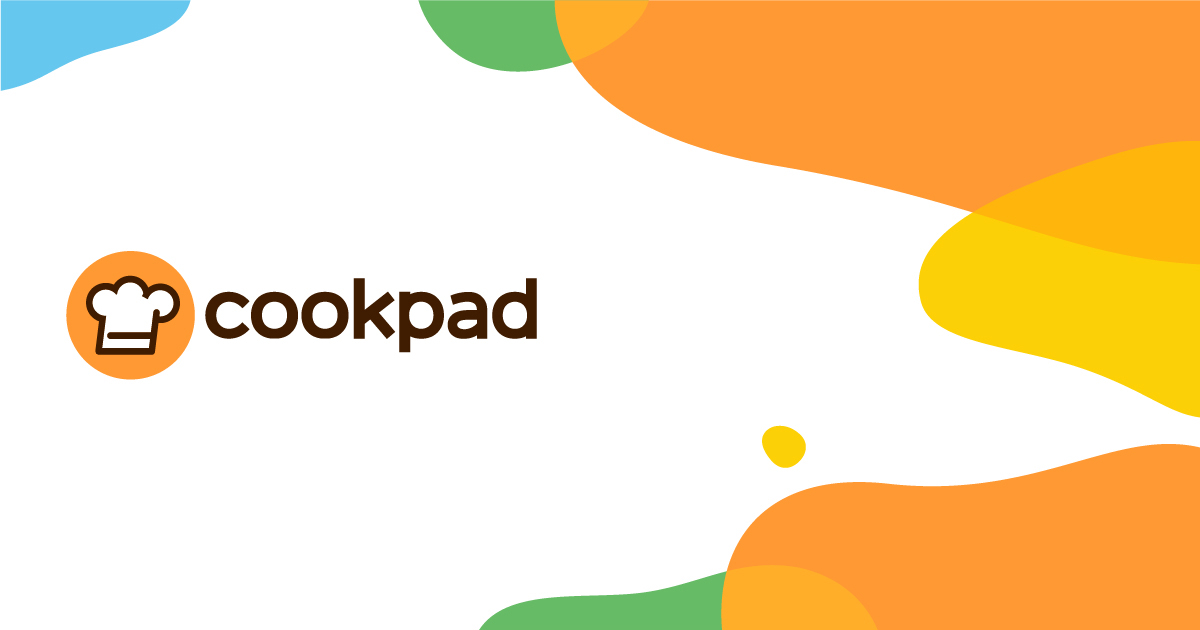
クックパッドがコーポレートブランドデザイン「Organic」を策定し、オリジナルフォント「Cookpad Sans」を作成
クックパッドは、ミッションである「毎日の料理を楽しみにする」をより視覚的、感覚的に伝えることを目的に、コーポレートブランドデザイン「Organic」の策定および、オリジナルコーポレートフォント「Cookpad Sans」の作成を行ったことを2022年7月21日に発表した。
新たなコーポレートブランドデザインは、柔らかで、温かみのある様々な形状/有機的(Organic)な色面の構成により、多様性を受け入れるクックパッドのプラットフォームの中で、つくり手が楽しんでいる躍動感を表現されている。
「Cookpad Sans」の作成はフォントワークスが協力しており、コーポレートブランディングをデザインの力で牽引し、ミッションである「毎日の料理を楽しみにする」をより多くの人に伝えていく。
あわせてOrganicを適用した新しいコーポレートサイトもリリースした。
コーポレートブランドデザイン策定の背景
クックパッドでは「毎日の料理を楽しみにする」をミッションとし、世界74カ国、32言語で提供している料理レシピ投稿・検索サービス「クックパッド」をはじめとした、料理にまつわる課題を解決する事業を展開している。その中で、今まで以上に迅速にミッション実現に近づくためには、その背景にある当社の思いや、さまざまなつくり手が楽しんでいる姿を、より多くの人に伝え、共感していただく必要があると考え、「多様なつくり手を受け入れ、つながることで生まれる『料理の楽しさ』を感じさせるデザイン」をコンセプトに、新たなコーポレートブランドデザイン「Organic」の策定および、オリジナルコーポレートフォント「Cookpad Sans」を作成した。
あわせてOrganicを適用した、新しいコーポレートサイトを公開している。
コーポレートブランドデザイン「Organic」
柔らかで、温かみのある様々な形状/色による有機的(Organic)な色面の構成による、クックパッドのコーポレートブランドデザインを策定した。多様性を受け入れるクックパッドのプラットフォームの中で、つくり手が楽しんでいる躍動感を表現している。
オリジナルコーポレートフォント「Cookpad Sans」
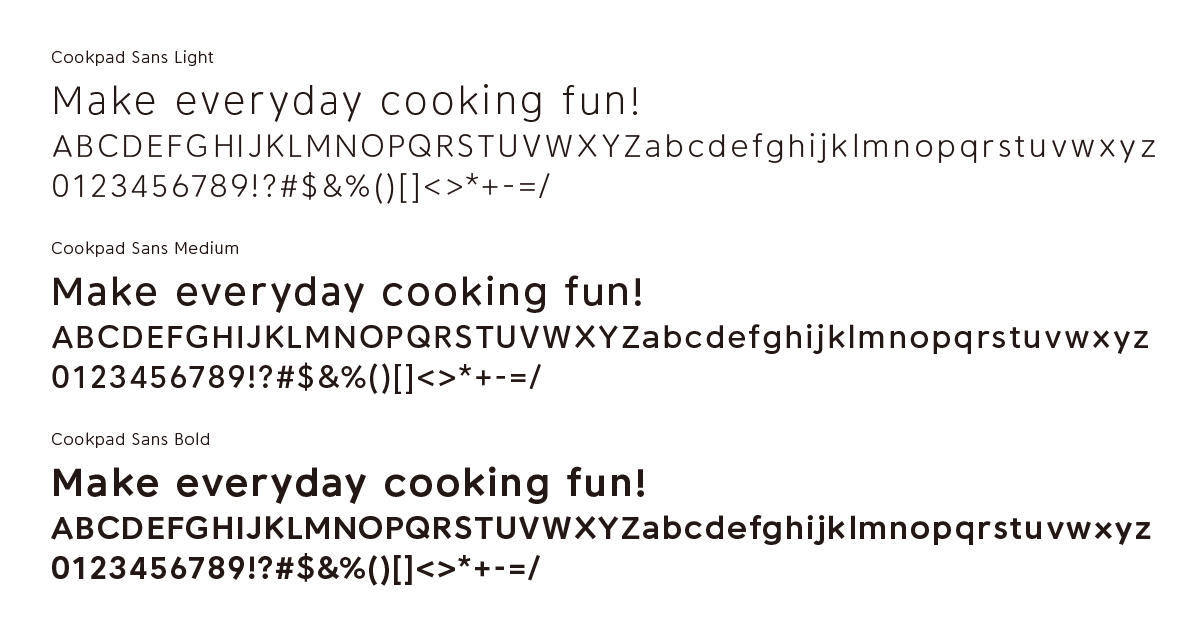
クックパッドのロゴタイプフェイスを起点とした欧文フォントを、フォントワークスに協力により、作成した。
新しいコーポレートサイト
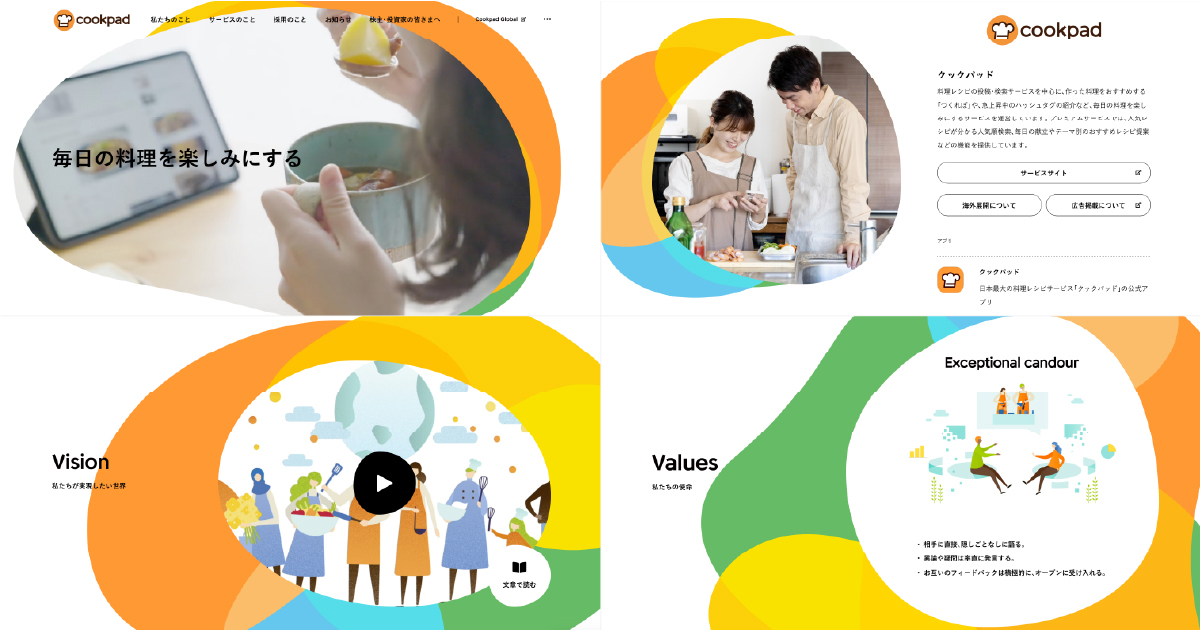
オブジェクトが有機的に動くことで、コーポレートブランドデザインのコンセプトである「多様なつくり手を受け入れ、つながることで生まれる『料理の楽しさ』を感じさせるデザイン」のサイトに一新した。
ミッションやビジョンだけではなく、今まで対外的に公開することが少なかったTruths(事業の考え方)やValues(個人の行動規範)も合わせて伝えることで、クックパッドが目指す世界と、その実現に向けてどのように考えで事業に取り組んでいるかを紹介している。